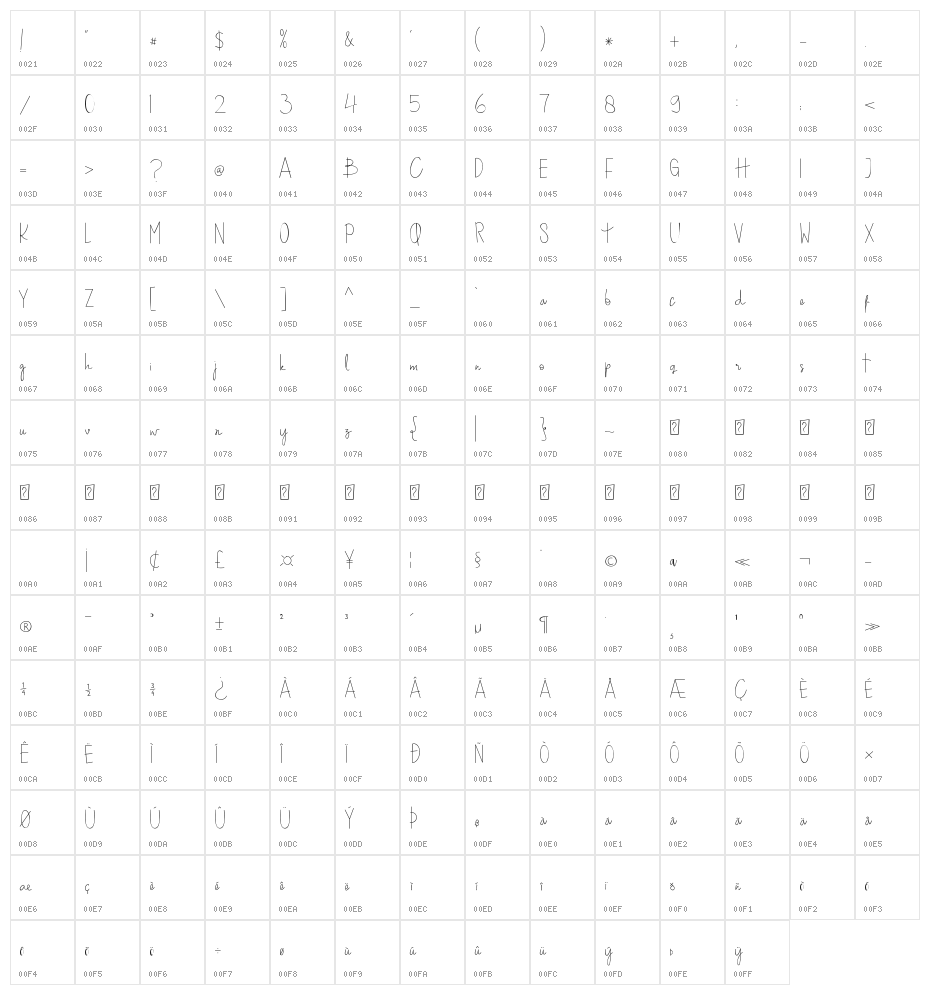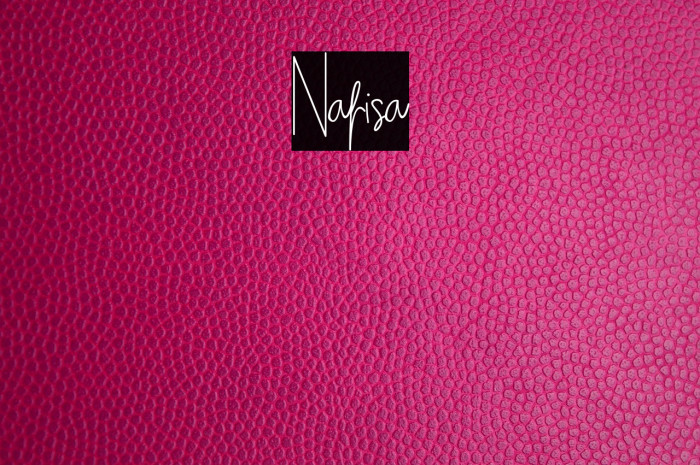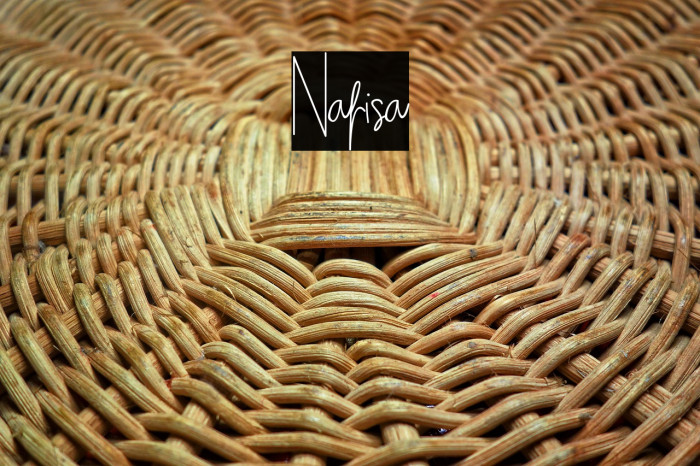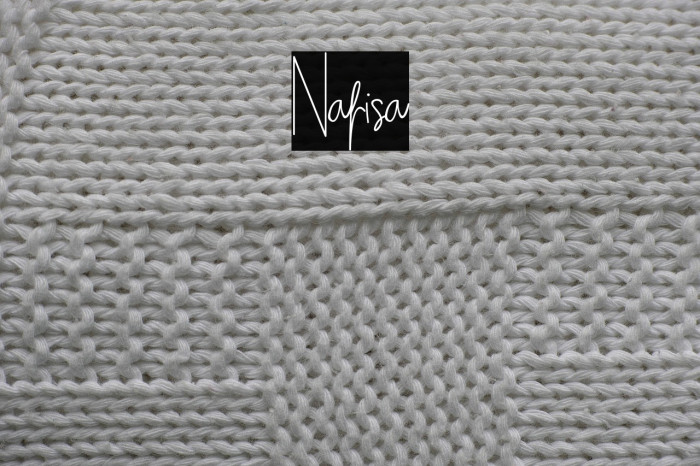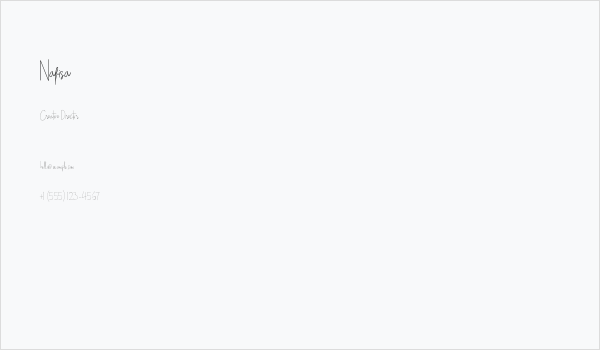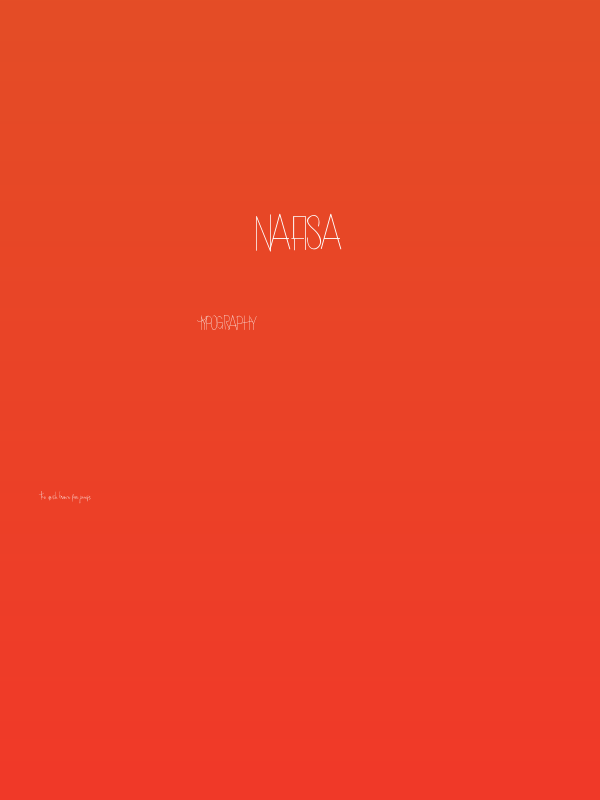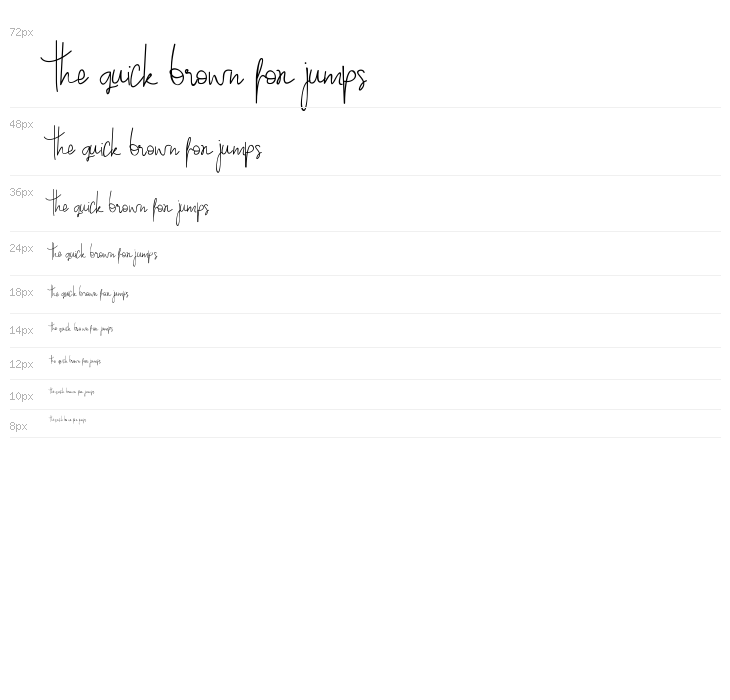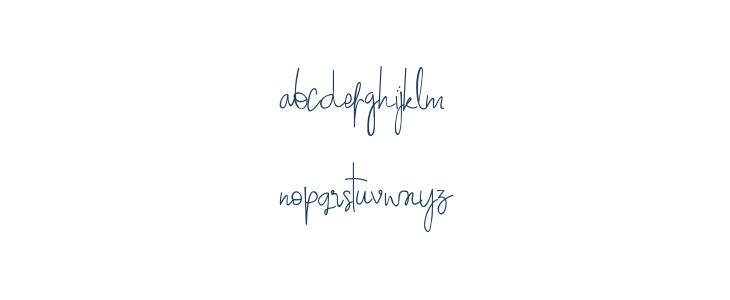
Nafisa Font
| Caso d'uso | Logos, Headlines, Creative projects |
| Progetti proposti | Ideal for creative projects such as greeting cards, invitations, personal branding, and artistic posters. |